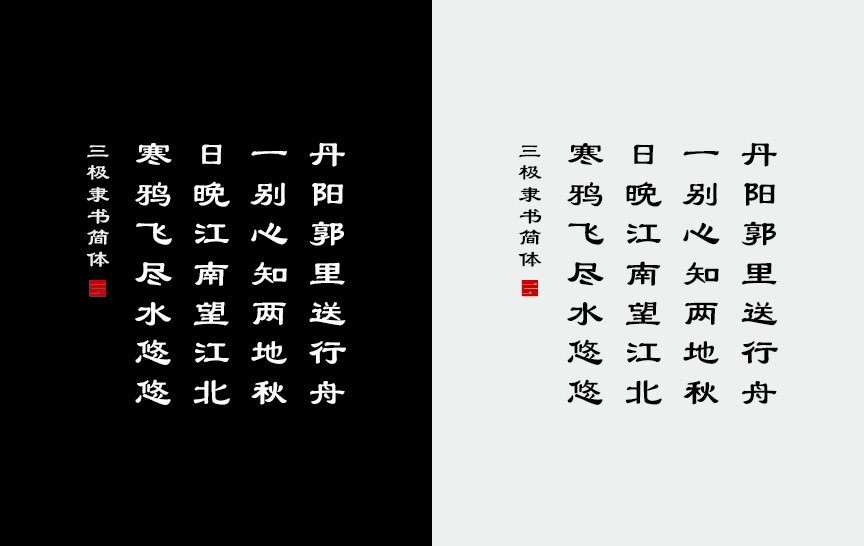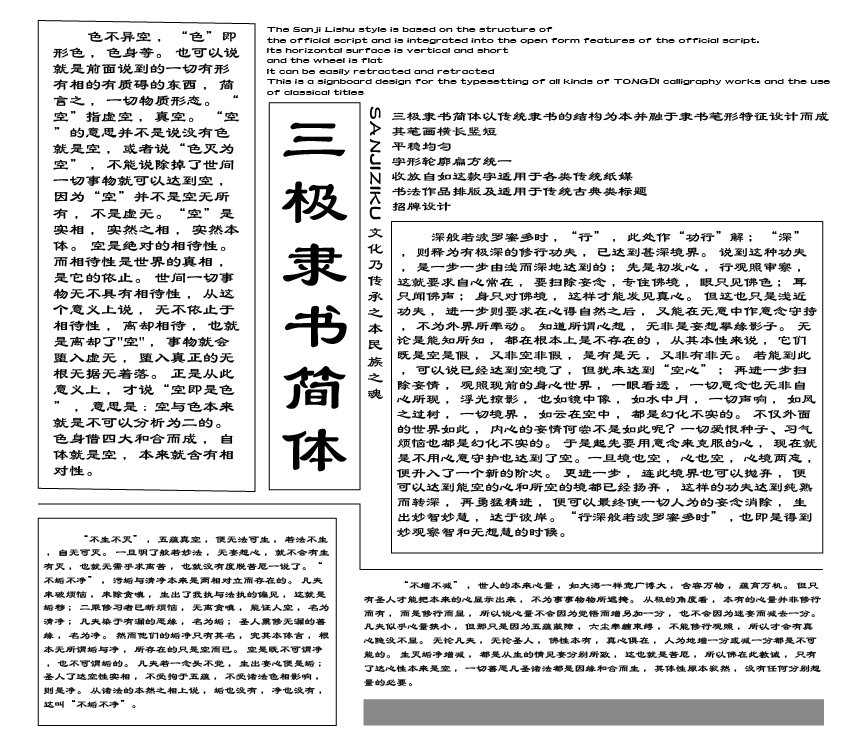
三级隶属简体 | 隶书字体授权 一款隶书字体
字体名称:三极隶书简体                  版权所有:三极字库
设计师:蔡荣富                               所属分类:隶书
字体介绍:
三极隶书简体以传统隶书的结构为本并融于隶书笔形特征设计而成,其笔画横长竖短,平稳均匀,字形轮廓扁方统一,收放自如。这款字适用于各类传统纸媒,书法作品排版及适用于传统古典类标题、招牌设计。
适用媒介:报纸、杂志、书籍、广告、店招、标志、宣传册、字幕、包装、屏幕显示。